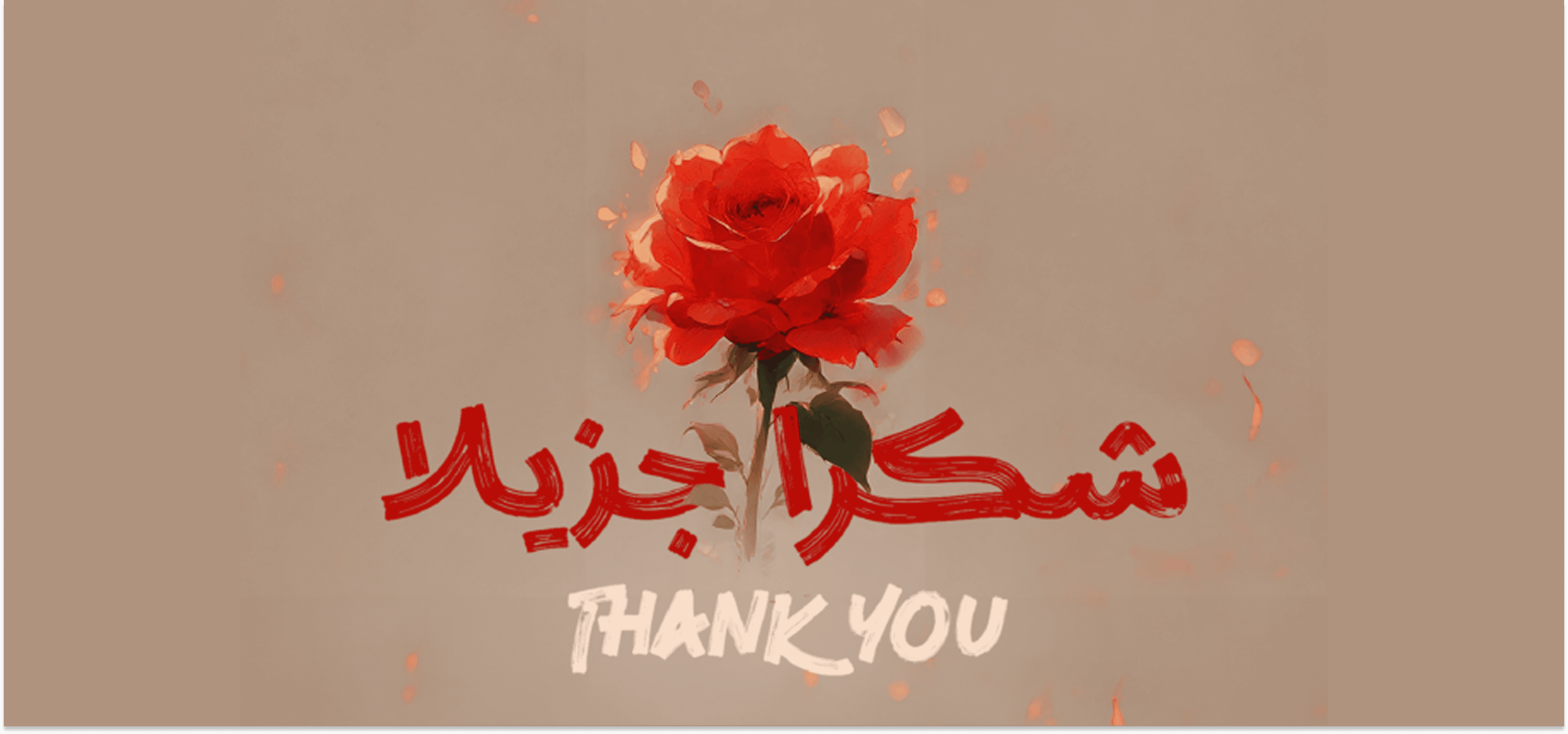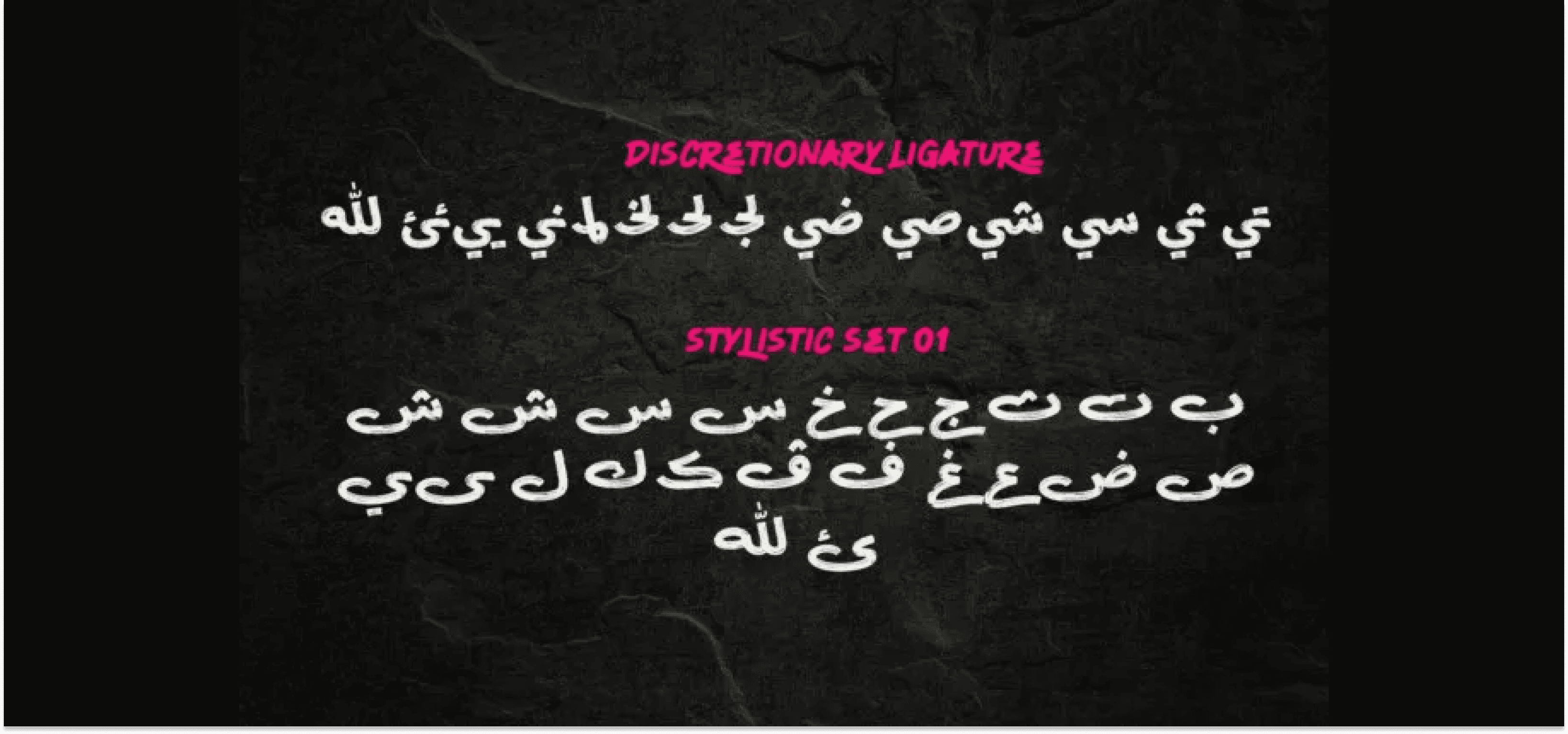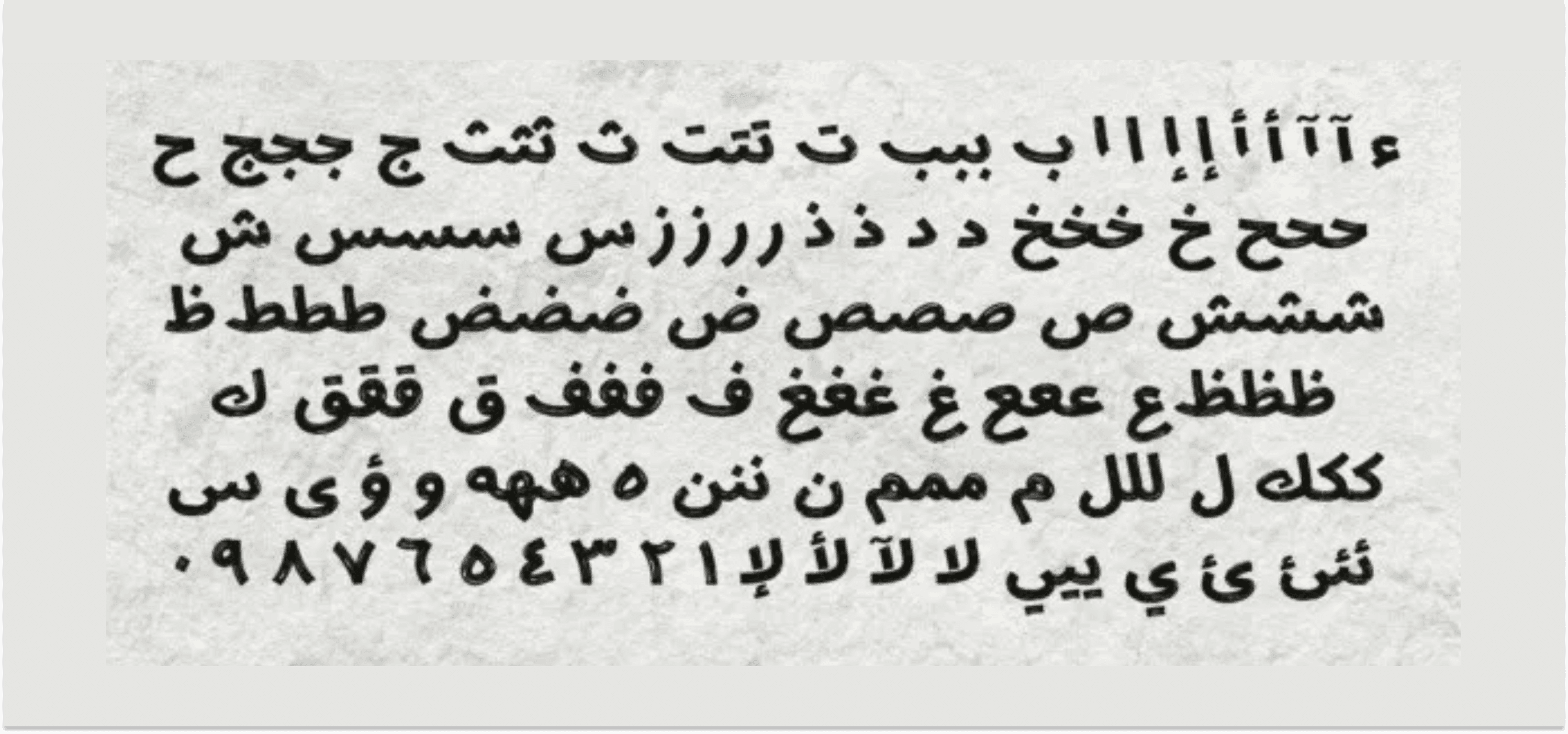
هو خط فرشاة عربي يتميز بإضافة موسعة لمحارف اللغة العربية، مما يعزز من مرونته وقدرته على التكيّف مع احتياجات لغوية وتيبوغرافية متنوعة.
تتضمن هذه الإضافة محارف إضافية وتشكيلات دقيقة، مما يسمح بتمثيل أكثر دقة للهجات الإقليمية واللغات التي تستخدم الحرف العربي.
يدعم الخط نطاقًا أوسع من الأعمال الأدبية والعلمية، ويُسهم في رفع دقة النشر والنسخ الأكاديمي. كما يُحسِّن تجربة التواصل الرقمي من خلال دعم أفضل لعرض النصوص على الأجهزة الحديثة.
بشكل عام، تُعد هذه التوسعة تطورًا مهمًا يفيد اللغويين، المعلمين، والمجتمعات العالمية التي تعتمد على الحرف العربي.